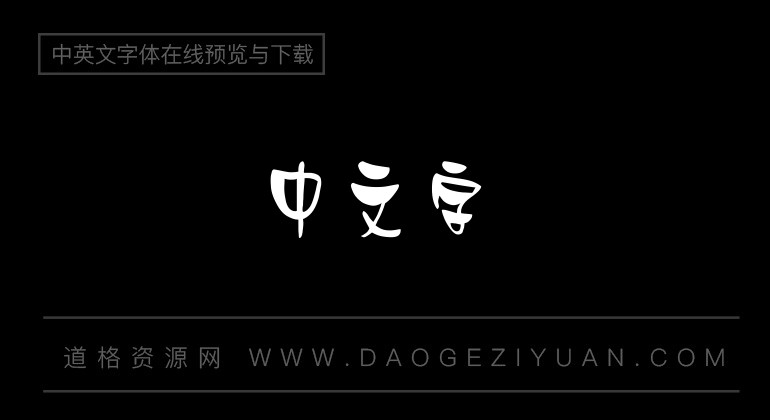
金梅公主美工国际码字体
金梅公主美工国际码字体是由金梅公主美工国际有限公司推出的一款国际码字体,它具有非常流畅的设计,整体构图清晰,符号精确,更能够体现出字体的精美程度,而且它的字体特色更加突出,更具有深刻的视觉效果,可以为您的设计作品增添更多的色彩,让您的设计作品更加精彩。
金梅公主美工国际码字体是一款非常不错的手写艺术字体,具有很好的视觉感,适合于文化类的宣传设计、商业类品牌的广告和产品包装设计以及个性化文字排版等较多场景。